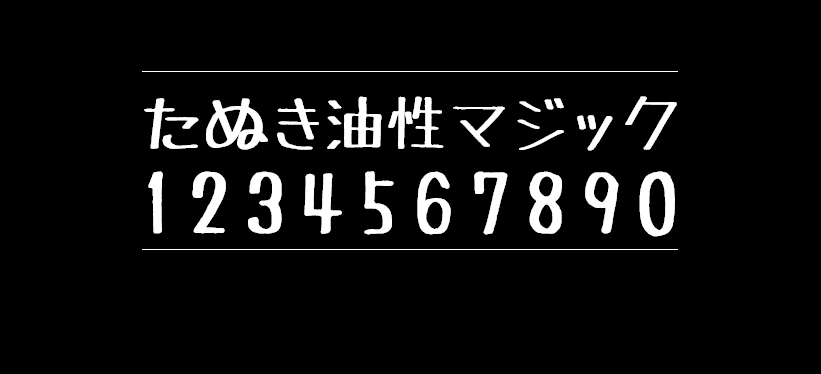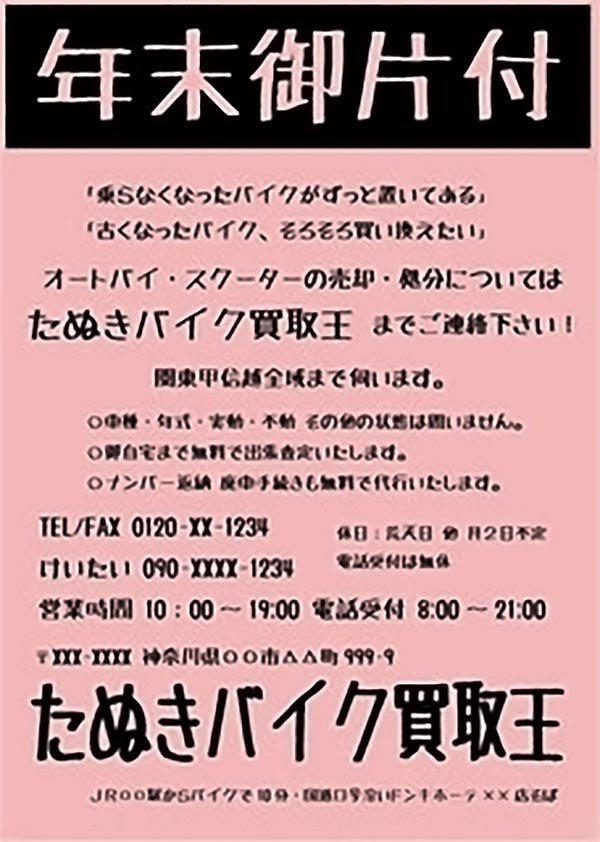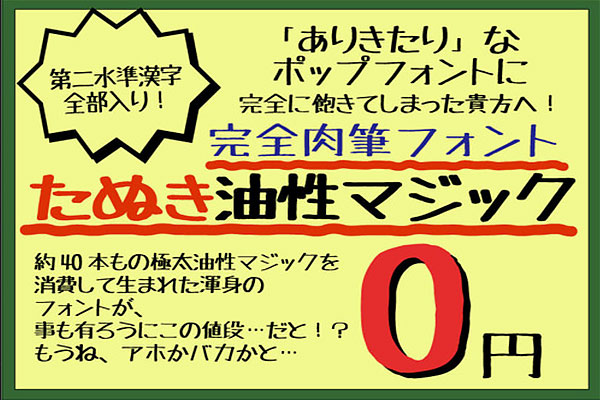
马克笔手绘体
马克笔手绘体( 日文名: たぬき油性マジック,英文名Tanuki Permanent Marker ),电脑还没有普及的时候,如果要画壁报、制作海报都会手写,很多人对于拿马克笔手绘 POP写一套,能以各种不同颜色画笔写出很动感又吸引注目的艺术字体。如果你不会写 POP 又希望能够使用类似效果,不如直接找个字型会更快更轻松。马克笔手绘体是一款日本网站提供的免费字型,如同前面所说,TanukiMagic 字型风格和马克笔手绘的 POP 效果如出一辙,因为日文字型很多都涵盖繁体汉字部分,套用到中文也不太会出现缺字问题,但是简体的话缺字较多。